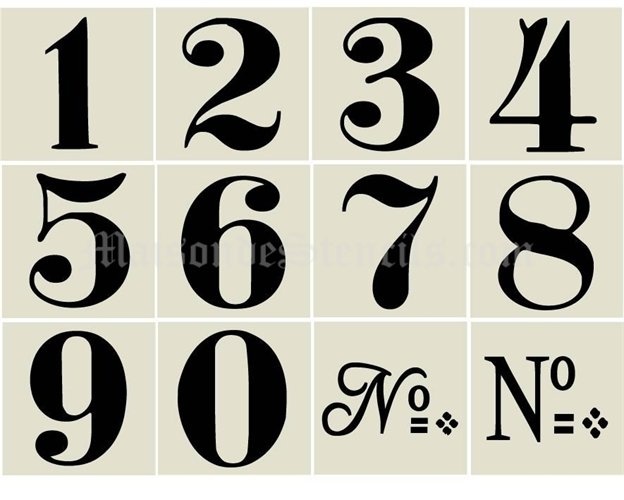
При рассмотрении типографики веб-сайта основное внимание уделяется буквам по понятным причинам.
Однако цифры тоже имеют решающее значение.
Вы должны особенно помнить о цифровом шрифте при разработке инфографики, календарей или других дизайнов, содержащих числа.
Только с помощью правильного числового шрифта вы сможете придать своему дизайну или веб-сайту профессиональный и художественный вид. К счастью, числовых шрифтов много, и выбрать правильный может быть непросто.
Мы упростили вам задачу с помощью этого списка лучшие числовые шрифты.
1. Номера комнат Dione отображают семейство шрифтов
Dione Room Numbers Display — это неалфавитный шрифт с засечками. Он фокусируется исключительно на числовых и валютных символах.
Окрашенные номера гостиничных номеров вдохновлены шрифтом. Это же хорошо видно по внешнему виду! Если вы ищете дисплейный шрифт, рассмотрите Dione Room Numbers Display.
2. Дропгрей
Если вы хотите добавить элегантности в свой дизайн, ваш поиск должен закончиться на Dropgray. Этот шрифт поддерживает следующее:
- Номера
- Символы
- Прописные и строчные буквы
Сарид Эзра — создатель Dropgray, который идеально подходит для любого высококлассного дизайна.
Кроме того, шрифт поддерживает многоязычную функцию, что является бонусом.
Используйте Dropgray, если хотите добавить в свой дизайн нотку 70-х.
3. Okami
Okami — это шрифт кисти, идеально подходящий для современного, но элегантного дизайна. УТП Okami заключается в том, что он выглядит как нарисованный от руки шрифт с оттенком грубого края.
Вы можете использовать Okami, если вам нужно записать:
- Номера
- Верхний регистр
- Многоязычные письма
- Пунктуация
Шрифт поддерживает множество альтернативных стилей для большинства букв.
4. Долото
Дрю Мелтон — дизайнер шрифта Chisel. Опять же, это неалфавитный шрифт, который можно использовать на витринах и плакатах.
Шрифт доступен в трех разных стилях. Мы рекомендуем этот шрифт, если вы хотите использовать в своем дизайне только сплошные цифровые символы.
5. Причуда
В соответствии со своим названием, Quirk — необычный шрифт. Кривые в цифрах делают этот шрифт уникальным.
Вы можете использовать шрифт Quirk для:
- Номера
- Специальные символы
- Все заглавные и строчные буквы чередуются между собой
Альтернативная коллекция шрифтов удобна для создания уникальных дизайнов.
6. Западная стойкость
Компания Western Grit, принадлежащая к семейству Serif, придает цифрам тревожный вид. Это нарисованный от руки шрифт, создающий ощущение старины.
Western Grit будет хорошо смотреться на вывесках и плакатах, которым нужен винтажный вид. Помимо цифр и символов, вы также можете использовать их для написания основных символов и знаков препинания.
7. Джессетто
Gessetto — идеальный шрифт для детских проектов. Исходя из семейства меловых шрифтов, USP Gessetto заключается в вариациях, которые он несет как по текстуре, так и по стилю.
8.
Числа Климента Этот шрифт вдохновлен Книгой образцов шрифтов 1838 года, которая была выдана дизайнеру Фондери Клементом.
Спиральный вихрь цифр придает шрифту Clement Numbers сущность.
9. Монотон
Визуальный стиль Monoton напомнит вашим читателям металлические шрифты 1930-х годов. Несмотря на то, что Monoton разработан для веб-браузеров, он лучше всего подходит для листовок.
Вы можете получить Monoton бесплатно.
Получить шрифт
10. Жак Франсуа Шэдоу
Cyreal, дизайнер Jacques Francois Shadow, черпал вдохновение для шрифта у Jacques Francois Rosart. Эффект тени текста выделяет его почти во всех средах.
Jacques Francois Shadow лучше всего подходит для дизайна с крупным шрифтом.
Получить шрифт
11. Комбинированный шрифт
CombiNumerals Font — это блочный шрифт для чисел. Вы можете использовать этот шрифт для создания номера круга.
Лучше всего подходит для разработки веб-графики и путеводителей.
Получить шрифт
12.
БермонBeurmon — это шрифт с закругленными краями и геометрическим оттенком. Вы можете использовать этот шрифт как для цифр, так и для символов. Однако, несмотря на то, что он имеет многоязычную поддержку, его можно использовать только для верхнего регистра.
Вы можете использовать Beurmon в письмах, требующих большого текста, таких как заголовки и тексты, используемые на обложках журналов.
13. тлеющие угли
Этот стиль шрифта для чисел доступен в двух разных стилях. Это крупный трафаретный шрифт, который помогает создавать эффектные заголовки.
Учитывая, что это большой текст, вы можете использовать Ember для создания постеров и листовок.
14. Хико Инлайн
Hikou Inline — красивый винтажный шрифт, который отлично подходит для заголовков. Помимо написания цифр, вы также можете использовать его для заглавных многоязычных букв.
Вы можете использовать уникальный дизайн Hikou Inline для создания постов в социальных сетях с эстетичным видом.
15. Кумар Один
Kumar One щеголяет широкими вертикальными штрихами с более тонкими горизонтальными линиями. Кроме того, угол 45 градусов в углах номера Kumar One делает их лучше.
Он выглядит чистым и декоративным одновременно, что в конечном итоге приводит к профессиональному виду.
Получить шрифт
16. Старый Стандарт ТТ
Что можно ожидать от Old Standard TT? Что ж, у многих он вызывает чувство ностальгии, возвращая их в 20 век.
Это смесь шрифтов с засечками и современных шрифтов без засечек. Шрифт выглядит чистым, и вы можете использовать его на веб-сайте, которому нужен минималистичный шрифт.
Получить шрифт
17. Нажмите Старт 2P
Press Start 2P — классный шрифт, который обязательно понравится геймерам. Пиксельный стиль шрифта делает его подходящим для разработки всего, что связано с игрой.
Вы можете бесплатно использовать Press Start 2P в Google Fonts.
Получить шрифт
18. Плохой сценарий
Не обманывайтесь названием этого шрифта.
Несмотря на то, что этот шрифт называется Bad Script, на самом деле это идеальный шрифт.
Когда вы используете Bad Script в числах, неровное основание цифры придаст дизайну уникальный вид.
Получить шрифт
19. Дэмион
Дэмион хорошо выглядит не только цифрами, но и буквами. Так что вы можете использовать его, если хотите создать легко читаемую работу.
Круглый и жирный край шрифта Damion делает его подходящим для всех веб-сайтов.
Получить шрифт
20. Малиновый текст
Crimson Text снова доступен в Google Fonts. Этот шрифт отличается простотой и элегантностью.
Независимо от того, хотите ли вы создать серьезный или повседневный дизайн, Crimson Text подходит благодаря чистым линиям.
Получить шрифт
21. Лато
Lato — это модный числовой шрифт из-за его чистого внешнего вида. Простой вид шрифта делает его подходящим для дизайна практически всего.
Если вы хотите написать большие числа в дизайне, рассмотрите Lato из-за его красоты, которая выделяется в больших текстах.
Получить шрифт
22. Варела Раунд
Как следует из названия, Varela Round — это круглый шрифт. Это дает непринужденный вид, и вы должны использовать его с небольшим размером шрифта.
Коэффициент читабельности Valera Round хороший, что делает его подходящим для длинных текстов и чисел.
Получить шрифт
23. Дисплей с засечками DM
Все в дисплее DM Serif говорит о мощности. Контрастность шрифта делает его подходящим для написания цифр, когда вы хотите что-то выделить.
DM Serif Display может легко доминировать в пространстве при использовании в дизайне. Поэтому используйте его только тогда, когда вы включаете на страницу ограниченное количество номеров, чтобы создать визуальную иерархию.
Получить шрифт
24. Баклан Гарамонд
Вы можете использовать Cormorant Garamond для включения цифр в заголовки или заголовки. Эстетический вид Cormorant Garamond делает его пригодным для дизайна продуктов, но не для длинных текстов.
Получить шрифт
25.
ПолужирныйЦена УТП BoldPrice заключается в эффекте дерева его полужирной версии. Он также предлагает версию с обычным весом.
BoldPrice имеет только превосходящие числа и лучше всего подходит для меню ресторана и написания цен.
26. Новая Гельветика
Разработанный еще в 1957 году, Neue Helvetica до сих пор популярен благодаря своему классическому стилю. Кроме того, шрифт придает современный вид классической Helvetica.
Получить шрифт
27. София Про
Он принадлежит к семейству геометрических шрифтов без шрифтов. Sofia Pro — популярный шрифт среди графических дизайнеров.
Несмотря на то, что Sofia Pro выглядит современно, она также элегантна. Шрифт лучше всего подходит для цифр в мелком тексте. Кроме того, вы можете использовать его при разработке мобильных приложений или визитных карточек.
Получить шрифт
28. Копс
Copse — очень читабельный шрифт благодаря своему классическому виду. Несмотря на то, что многие люди не знают о Copse, это шрифт с уникальными функциями.
Контрастный дизайн Copse делает его подходящим для ведения блогов.
Получить шрифт
29. Выпускной
Мы рекомендуем вам использовать Graduate для всего, что связано с образованием. Блочный дизайн Graduate делает его подходящим для любой работы в колледже.
Шрифт Graduate доступен бесплатно в Google Fonts.
Получить шрифт
30. Поппинс
Поппинс принадлежит к семейству шрифтов без засечек. Он подходит для дизайна практически всего из-за его превосходного дизайна фигуры.
Шрифт поддерживает множество вариаций веса. Вы можете поэкспериментировать с вариациями и остановиться на той, которая подходит дизайну.
Получить шрифт
15 лучших шрифтов для оформления цифр
Посмотрите эти 15 лучших шрифтов для цифр ! Эти шрифты идеально подходят для любого проекта и представлены в различных стилях в соответствии с вашими потребностями. Ищете ли вы традиционный шрифт или что-то более современное, мы предоставим вам все необходимое.
Так чего же вы ждете?
Начните просмотр и выберите идеальный шрифт для своего следующего проекта!
Что такое числовые шрифты?
Числовые шрифты — это тип шрифта, специально предназначенный для чисел. Эти шрифты можно использовать для различных целей, например, для отображения числовых данных или создания нумерованных списков.
Числовые шрифты бывают самых разных стилей, от традиционных и консервативных до современных и необычных. Независимо от того, что нужно вашему проекту, есть числовой шрифт, который идеально подходит для вас.
Так зачем использовать числовой шрифт? Причин несколько.
Во-первых, цифровые шрифты облегчают чтение и понимание данных. Если вы показываете числа в отчете или презентации, использование четкого и разборчивого шрифта может помочь вашей аудитории легче понять информацию.
Кроме того, числовые шрифты могут добавить визуальный интерес к спискам и текстовому содержимому.
Если вы хотите добавить немного индивидуальности своему письму, использование забавного и уникального числового шрифта — отличный способ сделать это.
15 лучших числовых шрифтов для оформления чисел
Как можно использовать числовые шрифты?
Существует множество способов использования числовых шрифтов, чтобы ваши документы и проекты выглядели более профессионально. Вот некоторые из лучших способов использования числовых шрифтов:
1. Используйте числовые шрифты для списков
Цифровые шрифты могут быть отличным способом сделать списки более привлекательными. Например, при создании маркированного списка можно использовать числовой шрифт, чтобы каждый маркер выделялся больше.
2. Используйте числовые шрифты для заголовков и подзаголовков
Цифровые шрифты также можно использовать для заголовков и подзаголовков, что поможет создать более иерархический вид документа или дизайна.
3. Используйте числовые шрифты для выносок и аннотаций
Цифровые шрифты можно использовать для выносок и аннотаций в документах и проектах.
Это может помочь сделать ваши выноски и аннотации более читабельными и понятными.
4. Используйте числовые шрифты для инфографики
Цифровые шрифты могут быть отличным способом добавить визуальный интерес к инфографике. Используя разные числовые шрифты для других элементов инфографики, вы можете создать более визуально привлекательную и информативную графику.
5. Используйте числовые шрифты для визуализации данных
Цифровые шрифты также можно использовать для визуализации данных. Используя различные числовые шрифты для других элементов визуализации данных, вы можете создать более визуально привлекательную и информативную графику.
6. Используйте шрифты с цифрами для слайдов презентации
Шрифты с цифрами могут быть отличным способом добавить визуальный интерес к слайдам презентации. Использование различных числовых шрифтов для других элементов слайда может сделать презентацию более визуально привлекательной и информативной.
7.
Используйте числовые шрифты для плакатов и листовокЧисловые шрифты также можно использовать для плакатов и листовок. Используя разные числовые шрифты для различных элементов вашего плаката или флаера, вы можете создать более визуально привлекательный и привлекающий внимание дизайн.
8. Используйте цифровые шрифты для дизайна веб-сайтов
Цифровые шрифты также можно использовать в веб-дизайне. Используя разные числовые шрифты для других элементов вашего веб-сайта, вы можете создать более привлекательный и удобный для пользователя веб-сайт.
9. Используйте числовые шрифты для дизайна электронной почты
Цифровые шрифты также можно использовать в дизайне электронной почты. Используя различные числовые шрифты для других элементов электронной почты, вы можете создать более визуально привлекательную и удобную электронную почту.
10. Используйте числовые шрифты для сообщений в социальных сетях
Цифровые шрифты также можно использовать в сообщениях в социальных сетях.
Используя разные числовые шрифты для различных элементов публикации в социальных сетях, вы можете создать более визуально привлекательную и удобную публикацию в социальных сетях.
1. Шрифты Clement Number
Шрифты Clement Number — одни из лучших шрифтов для чисел. Они хорошо читаются и отлично смотрятся в любом контексте. Ищете ли вы шрифт для финансового документа или дизайнерского проекта, шрифты Clement Number — отличный выбор.
При выборе шрифта для цифр необходимо учитывать несколько моментов. Во-первых, важна разборчивость. Шрифт должен легко читаться при любом размере. Во-вторых, шрифт должен хорошо работать в разных контекстах. Он должен иметь возможность адаптироваться к различным целям и видам использования. В-третьих, шрифт должен быть эстетичным. Он должен быть визуально привлекательным и дополнять общий дизайн проекта.
Шрифты Clement Number соответствуют всем этим критериям. Они очень разборчивы, адаптируемы и визуально привлекательны. Если вы ищете отличный шрифт для чисел, Clement Number Fonts должен быть в верхней части вашего списка.
Если вы ищете лучшее количество шрифтов, обратите внимание на BoldPrice! Наши шрифты специально разработаны для чисел и валюты, поэтому вы можете быть уверены, что ваш текст будет выглядеть великолепно. Кроме того, наши шрифты легко читаются и полностью настраиваются, поэтому вы можете создать именно тот вид, который вам нужен.
Так что проверьте BoldPrice сегодня и убедитесь, почему мы лучшие!
3. Семейство шрифтов для отображения номеров комнат DidoneDidone Семейство шрифтов для отображения номеров — один из лучших доступных шрифтов для номеров. Он идеально подходит для любого проекта, требующего элегантности, и поставляется с различными стилями на выбор. Семейство шрифтов Didone Room Numbers Display Font добавит нотку классности любому проекту.
4. Pumpkin Лучшие шрифты для чисел Pumpkin — один из лучших шрифтов для чисел.
Он легко читается и отлично смотрится как в большом, так и в маленьком размере. Тыква также является очень универсальным шрифтом, который можно использовать в самых разных дизайнерских проектах. Независимо от того, создаете ли вы дизайн на тему Хэллоуина или что-то более серьезное, Pumpkin — отличный выбор для вашего следующего проекта.
Если вы ищете лучшее количество шрифтов, обратите внимание на Gorga Grotesque. Этот шрифт идеально подходит для любого проекта, требующего цифр, будь то дизайн веб-сайта, презентация в PowerPoint или даже печатный документ. Самое приятное в Gorga Grotesque то, что он поставляется в разных стилях, так что вы можете найти идеальный шрифт для своего проекта. Нужен ли вам простой шрифт или что-то более сложное, Gorga Grotesque поможет вам.
6.Vaporfuturism OTF Retrowave Font Vaporfuturism — лучший числовой шрифт, который идеально подходит для любого проекта, требующего использования цифр в шрифтах.
Этот шрифт включает в себя широкий спектр цифр, как пропорциональных, так и моноширинных, которые обязательно удовлетворят потребности любого дизайнера.
Независимо от того, ищете ли вы шрифт для конкретного проекта или вам нужен универсальный цифровой шрифт, Vaporfuturism — отличный выбор.
7. Числа Winner Numbers Number FontsЧисловые шрифты Winner Numerals — это лучшие шрифты для чисел, и они идеально подходят для любого проекта, где требуются числа, от простой математики до более сложных уравнений.
Шрифт доступен с обычным и полужирным начертанием, так что вы всегда сможете найти идеальный вариант для своих нужд. И с более чем 100 различными персонажами у вас никогда не закончатся варианты.
8. Шрифт Robinson — один из лучших цифровых шрифтов. Он идеально подходит для установки больших чисел в тексте, а шрифт включает в себя различные стили для чисел. Шрифт доступен как в обычной, так и в полужирной версиях.
Robinson — универсальный шрифт, который можно использовать во многих проектах.
Hakuna Font — один из лучших числовых шрифтов. Он идеально подходит для любого документа или презентации, в которой используются числа. Шрифт Hakuna легко читается и имеет чистый современный вид, который выделит ваши документы среди остальных.
10. Summer 0f 76 — многострочный шрифт — лучший числовой шрифт. Он идеально подходит для придания изюминки вашим документам или веб-сайту. Этот шрифт также отлично подходит для создания заголовков и подзаголовков. Итак, если вы ищете лучший числовой шрифт, выберите Summer 0f 76 — Multi-Line Font.
11. Vintage Number Pack — лучший шрифт для цифр. Он идеально подходит для придания более стильного вида телефонным номерам, номерам кредитных карт и другим важным документам.
В этот пакет шрифтов входят:
— лучший числовой шрифт
— стильные шрифты
— легко читаемые шрифты
С помощью этого пакета шрифтов вы можете сделать свои документы более стильными и удобными для чтения.
12. Проверка цен – A Sign Painter Price Number Display ШрифтPrice Check – Шрифт для отображения цен от Sign Painter – один из лучших доступных шрифтов для чисел. Он идеально подходит для любого художника по вывескам или графического дизайнера, который хочет добавить нотку класса в свою работу. Этот шрифт также отлично подходит для тех, кто хочет создать винтажный или старомодный вид.
13. Old Jersey Bes Number Fonts Duo
Old Jersey Font Duo — один из лучших доступных цифровых шрифтов. Это отличный выбор для любого проекта, требующего стильного и современного вида. Шрифт идеально подходит для заголовков, логотипов и других проектов графического дизайна.
Это также отличный выбор для проектов веб-дизайна.
Шрифт доступен как с обычным, так и с полужирным начертанием, а также с курсивом и наклонным начертанием. Шрифт идеально подходит для любого дизайнерского проекта, требующего стильного и современного вида.
Это также отличный выбор для проектов веб-дизайна. Шрифт доступен как с обычным, так и с полужирным начертанием, а также с курсивом и наклонным начертанием.
14. Семейство шрифтов Bulk
Семейство шрифтов Bulk — один из лучших доступных цифровых шрифтов. Он легко читается, имеет чистый современный вид и идеально подходит для любого проекта, требующего простого элегантного шрифта.
— 100 % бесплатно для коммерческого использования
— Доступен в формате TTF
— Поддерживает наборы символов латиницы, кириллицы и греческого алфавита
— Идеально подходит для любого проекта, требующего простого элегантного шрифта
15. Серия шрифтов Peacemaker Best Number Fonts
Серия шрифтов Peacemaker — лучший способ придать вашим документам индивидуальность и изюминку.
С различными шрифтами на выбор вы можете найти идеальный вариант для любого проекта. От формальных до забавных, в серии шрифтов Peacemaker каждый найдет что-то для себя.
Лучше всего то, что все шрифты из серии Peacemaker Font Series очень высокого качества. Они добавят профессиональный вид любому документу и обязательно сделают вашу работу заметной. Поэтому, если вы ищете лучшее количество шрифтов, обязательно ознакомьтесь с серией шрифтов Peacemaker.
80+ лучших числовых шрифтов (БЕСПЛАТНО / Премиум) 2022
После всех замечательных наборов текстовых шрифтов, опубликованных на Hyperpix, теперь пришло время добавить немного искры в цифры и в вашем типографическом дизайне. Это оставляет нам эту превосходную коллекцию числовых шрифтов и множество вариантов.
Предлагая различные стили, этот выбор удовлетворит ваши потребности, от захвата детской веселой атмосферы до чего-то более причудливого и футуристического. Это полностью зависит от вас! Есть также классические образы, которые можно выбрать с помощью ретро-шрифтов, которые мы приготовили для вас.
В любом случае, с этими шрифтами ваша игровая графика, веб-сайты или другие коммерческие проекты будут на голову выше остальных.
Лучшие числовые шрифты
Нам потребовалась пара часов, чтобы зарегистрировать первоклассные числовые шрифты, но уникальный дизайн, который вы собираетесь создать с его помощью, того стоит. Мы включили бесплатные версии, а также премиум-версии, так что наслаждайтесь!
Thrifty Numerals
Шрифт Thrifty Numerals относится к серии цифр, разработанных в стиле ретро, и эти цифры можно комбинировать с другими буквами и с разными стилями, чтобы создать привлекательную и разнообразную тему.
Цена: Премиум
Номер Помпадур
Номер Помпадур, разработанный Энди Мангольдом, является одним из идеальных шрифтов для крупных чисел. Этот дисплейный шрифт бесплатен только для личного использования и подходит для многих дизайнов. Этот шрифт лучше всего использовать в больших размерах.
Цена: бесплатно
Road Rage
Road Rage, разработанный Юссефом Хабчи, является последним числовым шрифтом в нашем списке.
Этот рукописный шрифт бесплатен для личного использования и содержит только заглавные буквы. Создайте красивый дизайн с помощью Road Rage!
Цена: Бесплатно
Capture Smallz
Capture Smallz — это совершенно бесплатный шрифт для коммерческого и личного использования, представленный Magique Fonts. Этот армейский трафаретный шрифт имеет два файла шрифтов и жирный стиль. Используйте шрифт для оформления заголовков, логотипа и многого другого.
Цена: Бесплатно
Vintage Number Pack
Vintage Number Pack Шрифт выполнен в рисованном и винтажном стиле. Как вы можете видеть в письмах, есть ряд горизонтальных линий, которые вы можете придумать с комбинацией шрифтов и предоставить несколько привлекательных плакатов и логотипов для аудитории.
Цена: Premium
TS Block
TS Block — один из шрифтов Sans Serif Number, разработанный Стивом Феррерой. Этот сверхсжатый полужирный шрифт содержит только заглавные буквы и идеально подходит для упаковки, вывесок, баннеров, заголовков и других элементов дизайна.
Цена: Бесплатно
Стреляй на поражение
Стреляй на поражение — причудливый декоративный шрифт, разработанный Владимиром Николичем. Этот шрифт поставляется с двумя весами и создает потрясающий вид для ваших работ.
Цена: Бесплатно
Nikolas & Pine
Nikolas & Pine — причудливый мультяшный шрифт, представленный Khurasan. С этим шрифтом. вы получите два файла шрифтов, заглавные буквы, цифры и основные знаки препинания. Обратите внимание, что шрифт бесплатен только для личного использования.
Цена: Бесплатно
BoldPrice цифры валюты
BoldPrice цифры валюты шрифт, как следует из названия, подходит для бизнеса и банковских заданий, и вы можете использовать эти шрифты в графических изображениях наряду с буквами и чековыми суммами.
Цена: Премиум
Varsity
Varsity, представленный Brøderbund Software, представляет собой модный шрифт старой школы.
Этот шрифт с заглавными буквами имеет уникальный стиль и включает в себя цифры, знаки препинания и символы. Varsity — один из числовых шрифтов, который будет хорошо смотреться на многих ваших проектах.
Цена: Бесплатно
PaybAck
PaybAck — модный бесплатный шрифт для личного использования. Шрифт разработан Jayde Garrow и имеет смелый стиль. Попробуйте!
Цена: Бесплатно
Северная армия
Северная армия — жирный армейский трафаретный шрифт, созданный Woodcutter. Этот причудливый шрифт включает только заглавные буквы и хорошо подходит для многих дизайнов дисплеев, таких как заголовки, баннеры и многое другое.
Цена: Бесплатно
Freshman
Freshman, разработанный Уильямом Бойдом, является одним из абсолютно бесплатных шрифтов Number. Этот шрифт старой школы имеет причудливый смелый дизайн. Первокурсник предоставляет только заглавные буквы. Проверьте этот шрифт!
Цена: Бесплатно
Sketch 3D
Sketch 3D — причудливый мультяшный шрифт, созданный Галдино Оттеном.
Этот шрифт может создавать трехмерный вид, он бесплатен для некоммерческого использования и включает прописные и строчные буквы. Вы можете использовать этот функциональный шрифт для многих дизайнов.
Цена: Бесплатно
Правдивая ложь
Правдивая ложь, разработанная Джонатаном С. Харрисом, выполнена в причудливом стиле ужасов. Обратите внимание, что этот шрифт с заглавными буквами бесплатен только для личного использования, а для его коммерческого использования вам необходимо получить лицензию.
Цена: Бесплатно
Auto Techno
Auto Techno — техно-шрифт с двумя файлами шрифтов, созданными EyeCone. Этот шрифт с заглавными буквами предназначен только для личного использования, если у вас нет лицензии. Вы можете использовать шрифт в самых разных дизайнах!
Цена: Бесплатно
Championship
Championship — шрифт старой школы, созданный imagex. Этот причудливый шрифт с заглавными буквами может создать уникальный вид и выделить ваш дизайн, попробуйте!
Цена: Бесплатно
Prisma
Если вы ищете один из совершенно бесплатных числовых шрифтов, обратите внимание на Prisma, разработанный Дитером Штеффманном.
Prisma — это модный заводной шрифт с двумя файлами шрифтов и множеством различных функций для широкого спектра ваших дизайнов.
Цена: Бесплатно
Рислинг
Рислинг — ретро-шрифт в причудливом стиле, созданный компанией Bright Ideas. Рислинг использует прописные и строчные буквы, цифры, знаки препинания и символы. Попробуйте этот уникальный шрифт!
Цена: Бесплатно
York Whiteletter
York Whiteletter Шрифт разработан Pilaster Davy. Этот ретро-шрифт имеет два файла шрифтов и упростит разработку баннеров и логотипов. В этом шрифте также присутствуют лигатуры, росчерки и различные орнаменты.
Цена: Бесплатно
Легенда героев
Легенда героев, представленная imagex, имеет два разных веса. Этот причудливый комический шрифт содержит только заглавные буквы и создает великолепный вид для ваших дизайнерских проектов.
Цена: Бесплатно
Крутые девчонки
Следующий числовой шрифт, который я хочу вам представить, это Крутые девчонки, разработанный Томом Уайтом.
Оцените уникальный стиль этого причудливого шрифта.
Цена: бесплатно
Outrun future
Outrun future, представленный PressGang Studios, включает в себя три удивительных веса. Этот комический шрифт содержит только заглавные буквы и предназначен только для личного использования.
Цена: Бесплатно
Sketch College
Sketch College, разработанный Галдино Оттеном, представляет собой шрифт старой школы с лицензией только для некоммерческого использования. Пытаясь создать уникальный образ, попробуйте этот шрифт!
Цена: Бесплатно
Pincoya Black
Pincoya Black — один из числовых шрифтов, разработанный Даниэлем Эрнандесом. Этот сверхжирный шрифт поставляется с лицензией на коммерческое использование. Попробуйте, шрифт вам понравится!
Цена: Бесплатно
Impact Label
Impact Label — декоративный шрифт от Tension Type. Этот шрифт имеет два файла шрифтов и придает вашему дизайну необычный вид.
Impact Label — полнофункциональный шрифт; попробуйте!
Цена: Бесплатно
Penguin
Penguin — причудливый шрифт, созданный Brixdee. Шрифт на 100% бесплатный и функционален для разных дизайнов. Получите это и наслаждайтесь этим!
Цена: Бесплатно
Street Cred
Еще один из совершенно бесплатных числовых шрифтов — это Street Cred, созданный Typodermic Fonts. Этот причудливый ретро-шрифт хорошо подходит для графического дизайна, игровой графики, логотипов, дизайнов футболок, вывесок и многого другого.
Цена: бесплатно
Плохая кома
Bad Coma — искаженный шрифт, созданный imagex. Этот жирный сильный шрифт бесплатен только для некоммерческого личного использования. Bad Coma — хороший выбор для заголовков, баннеров, вывесок и многих других дизайнов.
Цена: Бесплатно
Коробка для
Коробка для, представленная junkohanhero, имеет три файла шрифтов и необычный стиль.
Этот искаженный шрифт содержит только заглавные буквы и может использоваться во многих дизайнах. Получите шрифт, вам понравится!
Цена: Бесплатно
Action Comics
Action Comics с двумя файлами шрифтов представлен imagex. Этот причудливый комический шрифт содержит только заглавные буквы и бесплатен для некоммерческого использования. Попробуйте этот шрифт!
Цена: Бесплатно
Совершенно секретно Штамп
Совершенно секретно Штамп, разработанный Галдино Оттеном, представляет собой причудливый трафаретный шрифт, идеально подходящий для заголовков, баннеров и многих других элементов дизайна. Этот шрифт, предназначенный только для личного использования, содержит буквы верхнего и нижнего регистра, цифры, знаки препинания и символы.
Цена: бесплатно
Маркер любви
Маркер любви, созданный Дарреллом Фладом, имеет 4 файла шрифтов и причудливый комический стиль.
Этот шрифт с заглавными буквами бесплатен для некоммерческого использования и идеально подходит для различных дизайнерских проектов. Это один из числовых шрифтов, который я рекомендую вам проверить!
Цена: Бесплатно
Barcade
Barcade от Iconian Fonts — универсальный шрифт с 18 файлами шрифтов. Этот причудливый ретро-шрифт создает уникальный образ. Не смотрите дальше, получите шрифт!
Цена: Бесплатно
Brush Pains
Brush Pains, разработанный Джонатаном С. Харрисом, — красивый причудливый шрифт только для личного использования. Получите этот шрифт для своего следующего проекта и наслаждайтесь им!
Цена: Бесплатно
Xilosa
Xilosa — еще один числовой шрифт, который будет в нашем списке. Этот шрифт разработан Атила Миланио. У символов красивые края и правильный геометрический шрифт. шрифт удобочитаемый и выглядит современно, попробуйте!
Цена: Бесплатно
KG Counting Stars
KG Counting Stars, разработанный Кимберли Гесвейн, — это бесплатный шрифт для некоммерческих работ и дизайна.
Этот причудливый декоративный шрифт состоит только из заглавных букв, и его стиль может привлечь внимание аудитории. Получите шрифт!
Цена: Бесплатно
Square Kids
Square Kids — это совершенно бесплатный шрифт, созданный Grafito Design. Этот декоративный шрифт идеально подходит для создания логотипов для детской комнаты и многих других дизайнов. Создайте красивый дизайн с Square Kids!
Цена: Бесплатно
Mickey’s School
Mickey’s School — шрифт старой школы, созданный imagex. Этот причудливый шрифт имеет два файла шрифтов и включает лицензию на некоммерческий дизайн. Вы получите все заглавные буквы и цифры; Попробуй это!
Цена: Бесплатно
Real Fast
Real Fast, представленный Xerographer Fonts, является одним из шрифтов с размытыми жирными цифрами. Заглавные и строчные буквы обеспечены этим причудливым шрифтом. для коммерческого использования необходимо получить лицензию.
Цена: Бесплатно
Shoes Center
Shoes Center — комический шрифт, представленный Qkila. Это шрифт с заглавными буквами в причудливом стиле, который придает привлекательный вид вашим проектам. Попробуйте этот шрифт для заголовков, вывесок, упаковки, фирменного стиля и многого другого.
Цена: Бесплатно
Sho-Card-Caps
Sho-Card-Caps — один из 100% бесплатных цифровых шрифтов, представленных Nick’s Fonts. создайте ретро-стиль с помощью этого шрифта с заглавными буквами!
Цена: Бесплатно
Fine College
Fine College — великолепный красивый шрифт, разработанный Галдино Оттеном. Fine College — это шрифт, написанный только заглавными буквами, предназначенный только для личного использования; Возьми!
Цена: Бесплатно
Dat Box
Dat Box от Xerographer Fonts — идеальный декоративный шрифт, состоящий только из заглавных букв.
Dat Box хорош для заголовков, баннеров, вывесок, логотипов и многого другого.
Цена: Бесплатно
Детские блоки 9Шрифт 0035
Baby Blocks представлен компанией Creative. Этот декоративный шрифт может придать уникальный вид вашим проектам и произведениям искусства. Попробуйте этот полнофункциональный шрифт!
Цена: Бесплатно
Bills Mafia
Bills Mafia — жирный шрифт, разработанный Джейд Гарроу. Этот шрифт Old School содержит только заглавные буквы и имеет лицензию для личного использования. Проверьте этот причудливый шрифт!
Цена: Бесплатно
Райал Черный блок
A Ryal Black Block от Docallisme HAS Feat Dutsky — это бесплатный шрифт для благотворительного некоммерческого использования. Это красивый шрифт, попробуйте!
Цена: Бесплатно
Neon Disco
Neon Disco Шрифт, представленный Xerographer Fonts, имеет причудливый заводной стиль.
Для этого шрифта доступен только один вариант, но он охватывает широкий спектр дизайнов. Попробуйте Neon Disco, это один из числовых шрифтов, который вам понравится!
Цена: Бесплатно
Turnpike
Turnpike — жирный сжатый шрифт, созданный Font Diner. С помощью которого вы можете создать ощущение ретро для своих дизайнов. Этот причудливый шрифт содержит только заглавные буквы и придает элегантный вид вашим проектам.
Цена: Бесплатно
Doctor Punk
Шрифт Doctor Punk выполнен в причудливом стиле и представлен компанией Woodcutter. Ищете один из шрифтов Number с уникальным внешним видом? Посмотрите Доктора Панка.
Цена: Бесплатно
Race1 Brannt NCV
Race1 Brannt NCV, созданный Fontry, поставляется с 8 файлами шрифтов. Этот шрифт содержит только заглавные буквы, поэтому этот шрифт является хорошим вариантом для многих дизайнов дисплеев.
Цена: Бесплатно
Moonlightning
Moonlightning — один из жирных цифровых шрифтов, представленных Darrell Flood.
Для этого шрифта Sans Serif доступно четыре файла шрифтов, поэтому он охватывает несколько дизайнов. Получите его!
Цена: Бесплатно
Pricedown
Pricedown — это дисплейный шрифт с одним весом, опубликованный Typodermic Fonts. Этот полужирный шрифт абсолютно бесплатен для личного и коммерческого использования и поддерживает функции OpenType. Попробуйте, не пожалеете!
Цена: Бесплатно
Quantify
Quantify, представленный Sentype, представляет собой шрифт без засечек, бесплатный для личного использования. Этот базовый дисплейный шрифт содержит как прописные, так и строчные буквы с цифрами и знаками препинания.
Цена: Бесплатно
Longhaul
Шрифт Longhaul разработан Джеймсом Барнардо. Этот шрифт Sans Serif предназначен только для личного использования и поставляется с полным набором символов и различными функциями. Это может быть тот шрифт, который вы ищете, проверьте его!
Цена: Бесплатно
Jasmine Laslo
Jasmine Laslo — это бесплатный шрифт для личного пользования, представленный Checkered Ink.
Этот базовый шрифт без засечек содержит только заглавные буквы и создает привлекательный вид для ваших работ. Попробуйте и наслаждайтесь!
Цена: Бесплатно
Movie Letters
Еще один из совершенно бесплатных цифровых шрифтов — Movie Letters, созданный Bou Fonts. Этот базовый шрифт содержит только заглавные буквы. это может быть очень функциональный шрифт, попробуйте!
Цена: Бесплатно
Calendar Note TFB
Calendar Note TFB — это абсолютно бесплатный декоративный шрифт, представленный zanatlija. Оцените уникальный стиль этого бесплатного шрифта!
Цена: Бесплатно
Казино
Казино — один из универсальных числовых шрифтов, разработанный Владимиром Николичем. Для этого причудливого ретро-шрифта доступно 20 файлов шрифтов, и он бесплатен для личного использования. Это шрифт с заглавными буквами для вашего дизайна дисплея, получите его!
Цена: Бесплатно
Collegerion
Collegerion от Leonard Posavec – LeoSupply.
co – один из модных шрифтов старой школы. Это смелый причудливый шрифт для вашего личного дизайна. Проверьте Collegerion!
Цена: Бесплатно
Arenq
Arenq — совершенно бесплатный причудливый шрифт, представленный skomii. Стилистические альтернативы, лигатуры и многие другие функции предоставляются шрифтом. Arenq — шрифт с заглавными буквами. Попробуйте!
Цена: Бесплатно
Super Retro M54
Super Retro M54, созданный justme54s, представляет собой ретро-шрифт с двумя файлами шрифтов. Этот сжатый полужирный шрифт идеально подходит для дизайна футболок и логотипов, заголовков, баннеров и т. д. Super Retro M54 бесплатен для личного использования.
Цена: Бесплатно
Boston Traffic
Boston Traffic, созданный Виком Фигером, является одним из совершенно бесплатных числовых шрифтов с причудливым стилем. Этот шрифт поддерживает только заглавные буквы. Попробуйте его для логотипов, заголовков, баннеров, вывесок и многого другого.
Цена: Бесплатно
Backcountry
Backcountry от HENRIavecunK — смелый авантюрный шрифт в причудливом стиле ретро. Для коммерческого использования этого шрифта необходимо получить лицензию.
Цена: бесплатно
Copasetic
Copasetic производства Nick’s Fonts предоставляется бесплатно для коммерческого и некоммерческого использования. Если вы хотите создать ретро-дизайн, вам нужно проверить этот шрифт с заглавными буквами!
Цена: Бесплатно
Sui Generis
Sui Generis, созданный Typodermic Fonts, — это один из совершенно бесплатных шрифтов Sans Serif Number, который можно использовать для постеров, логотипов, заголовков, игровой графики, видеороликов, дизайна футболок и т. д. многое другое.
Цена: Бесплатно
Sports Ball
Sports Ball — это базовый дисплейный шрифт, созданный Zephram. Этот совершенно бесплатный шрифт имеет ультра-жирный стиль.
Все прописные буквы поддерживаются шрифтом. Этот шрифт вдохновлен спортивными майками.
Цена: Бесплатно
Retriv
Retriv — один из красивых числовых шрифтов, разработанный Владимиром Николичем. Для этого бесплатного шрифта доступны два разных веса с полужирным шрифтом. Этот шрифт поставляется в обычном и курсивном вариантах.
Цена: Бесплатно
Dream MMA
Dream MMA by i Remember Halloween — научно-фантастический техно-шрифт. Шрифт жирный и четкий и поставляется с лицензией для личного использования. Используйте его для дизайна одежды, упаковки, брендинга и многого другого.
Цена: Бесплатно
Full Pack 2025
Full Pack 2025 — квадратный техно-шрифт, представленный imagex. Этот шрифт с заглавными буквами предназначен только для личного использования. Получите шрифт и наслаждайтесь дизайном!
Цена: Бесплатно
NFS
Шрифт NFS, созданный Jltv, является абсолютно бесплатным научно-фантастическим шрифтом.
этот техно-шрифт заглавными буквами охватывает множество дизайнов, попробуйте!
Цена: Бесплатно
Inversionz
Inversionz, созданный Darrell Flood, представляет собой квадратный техно-шрифт с 8 файлами шрифтов. Обратите внимание, что этот универсальный полнофункциональный шрифт бесплатен только для личного использования. Это один из числовых шрифтов, который я рекомендую вам попробовать!
Цена: Бесплатно
The Led Display St
The Led Display St — это бесплатный шрифт для личного использования, разработанный Southype. Этот техно-шрифт содержит только заглавные буквы и придает вашим работам уникальный вид.
Цена: Бесплатно
NFL RedZone
NFL RedZone разработана Джейд Гарроу. Этот смелый шрифт придает привлекательный вид любому дизайну. Попробуйте!
Цена: Бесплатно
Saber Shark
Saber Shark — научно-фантастический техно-шрифт, созданный Iconian Fonts.
Это очень универсальный шрифт с 29файлы шрифтов. Предоставляются только заглавные буквы, поэтому шрифт будет хорошо смотреться на широком спектре дисплеев.
Цена: Бесплатно
Predataur
Predataur, опубликованный Iconian Fonts, включает 34 файла шрифтов. Этот техно-шрифт содержит только заглавные буквы и бесплатен для личного использования. Это ультра-жирный сжатый шрифт, попробуйте!
Цена: Бесплатно
Barbara
Barbara, разработанный Владимиром Николичем, — это бесплатный шрифт для личного использования. Этот техно-шрифт имеет жирный стиль и содержит только заглавные буквы. Используйте шрифт для заголовков, упаковки, брендинга, вывесок, баннеров и других дизайнерских проектов. Barbara — один из функциональных числовых шрифтов. Попробуйте!
Цена: Бесплатно
Digital 7
Digital 7, созданный Style-7, поставляется с 7 файлами шрифтов. Этот техно-шрифт имеет лицензию для личного использования и создает цифровой вид ваших дизайнов.
Цена: Бесплатно
Karmatic Arcade
Karmatic Arcade — один из совершенно бесплатных числовых шрифтов, разработанный Виком Фигером. Этот шрифт поддерживает только заглавные буквы, что может создать красивый цифровой вид. Наслаждайтесь созданием уникального образа!
Цена: Бесплатно
Neonize
Neonize, представленный Rayhan, является одним из всех бесплатных числовых шрифтов с заглавными буквами для личного и коммерческого использования. Вы должны попробовать этот шрифт для своего следующего творческого проекта!
Chintzy CPU BRK
V5 Prophit
V5 Prophit — это уникальный шрифт с тремя файлами шрифтов, созданными vFive Digital.